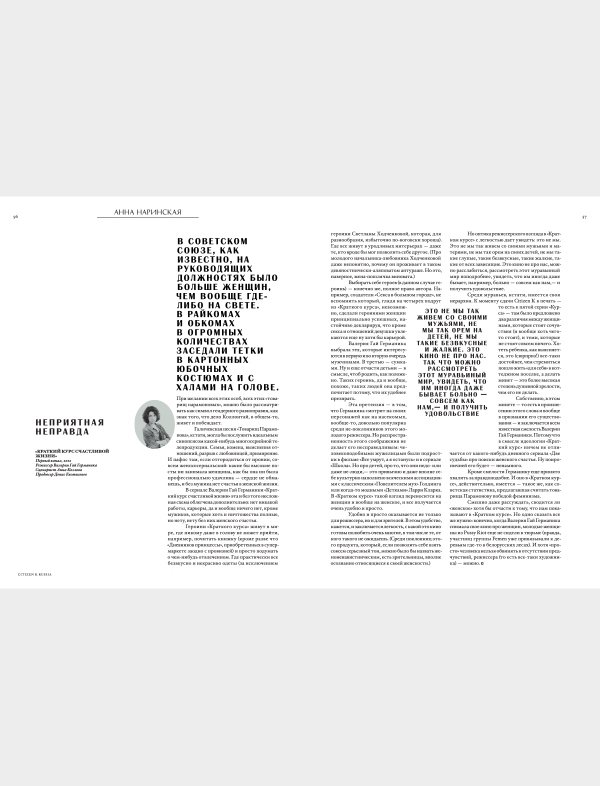
Если внутрицеховой диалог дизайнеров шрифта, типографов, графических и веб-дизайнеров более-менее налажен, то диалога с другими участниками издательского процесса — авторами, редакторами, издателями — почти не существует. Нам захотелось исправить эту ошибку.
АН: А можно задать такой вопрос? Моя личная жизнь была такая, что я жила и читала только книжки, например «Литературные памятники». Советские, но очень хорошие. Потом вдруг в какой-то момент появилось представление о том, что, кроме каких-то писателей, есть ещё что-то: панк-рок, всякие западные журналы — «Дейзд-энд-конфьюзд» (Dazed & Confused) или «Фейс» (The Face) и ещё. Там были такие шрифты, которые меня дико раздражали, но я понимаю, что это была их задача. Например, я помню, мне кто-то подарил — такой был невероятно щедрый подарок, и это, наверно, был 1999 год — подборку журнала «Фейс». Там всё было напечатано таким шрифтом. Как он называется? Шрифты состоят как бы из таких пенёчков.
ДЯ: Это пиксельный шрифт.
АН: Вероятно. Он был прямо такой, что ты ненавидел текст, который читал. Ты на него смотрел и думал: «Какая гадость! Зачем я это читаю?» Ты читал только потому, что тебе было интересно про Хлое Севиньи. И ты прямо бесился от этого. Сейчас я понимаю, что это, безусловно, было специально, это должно было так тебя раздражать. Помню, я всё время думала: «Всё хорошо в этом журнале, всё прекрасно, и темы меня интересуют, и что-то ещё, но это ужасно, зачем они это делают?»
ЮО: Представьте себе, что вы в семидесятых только что слушали группу The Beatles и вдруг почему-то видите группу Sex Pistols, а у них почему-то аппарат не настроен. А они его специально не настроили. Это, мне кажется, примерно то же самое.
АН: Я помню, как мы в «Коммерсанте» делали выпендрёжный журнал Citizen K. Там именно буквы становятся главным героем, и тогда непонятно, зачем Григорию Ревзину писать текст. Этот конфликт до сих пор для меня совершенно невыясненный.
КЧ: Дизайнеры замучили бесконечными редизайнами журналов. Ты привык к тому, что у тебя такая сетка, у тебя столько влезает на полосу. И тут очередной редизайн. «Мне надоело, всё надо поменять: новый шрифт, новое всё». Первые два номера, как правило, кровь из глаз. У меня когда-то, в бытность работы в «Плейбое», была его подшивка с 1961 по 1995 год. Как раз Дима Барбанель тогда работал арт-директором. Мы с ним любили рассматривать эту штуку. Интересно, что наборный шрифт, в общем, менялся год от года, но не чаще чем раз в пять-семь лет, а может быть, ещё реже. В основном всё биение времени задавалось акцидентными всевозможными штуками. Надо сказать, что, в принципе, даже средний Вася, когда ему показываешь разворот журнала издалека, не давая посмотреть, когда он вышел, может довольно точно назвать десятилетие просто по акцидентным шрифтам. Он может сказать: это шестидесятые, а это пятидесятые и так далее. Но по наборному шрифту это сказать совершенно невозможно. Нужно быть сильно вгруженным в тему, чтобы это угадать.
ФД: Заметим, что именно Citizen K стал тем журналом, о котором хочется вспоминать и которого не хватает. Я его как вещь именно осознаю.
Журнал CitizenK. Изображения из behance-аккаунта бывшего арт-директора Ждана Филиппова
АН: Вчера я отвезла своих родителей на некую далёкую дачу и, зайдя там в сортир, увидела стопку журналов Citizen K, которая лежала у унитаза. Я стала их листать и вспоминать, как это всё было. В частности, я помню ужас. Все это знают. На самом деле это борьба за то, что важнее, что первично — содержание или текст. Это каждый из нас знает. Приходит тебе «рыба» от дизайнера. Там написано: заголовок — два слова, подзаголовок — четыре слова, и ты хоть убейся, а выносы — строго три строчки. Ты думаешь, зачем все эти прекрасные люди, которых мы собирали, пишут все эти замечательные тексты, если дальше им говорят: «Ваш заголовок должен быть столько, подзаголовок столько, ваш текст столько, мысли столько». Потому что эпоха технической воспроизводимости вывела книгонаборщиков на совершенно другой уровень — раньше они были вообще людьми забитыми, им максимум разрешали буквицу красиво нарисовать, а дальше они бахали текст, как им сказали. Они стали изгаляться в дизайне, тем самым визуально привлекая людей плетением буквочек, и потихонечку вытеснять из массового сознания смыслы, заменяя их картинками. Именно дизайнеры, особенно из периодической печати, привели нас к этому клиповому сознанию отвратительному. Вы настоящие враги смыслов и своими красивыми шрифтами просто уничтожаете смысл.
ДЯ: А вы не чувствуете разницу жанровую, литературную, смысловую между заголовком в две строки и в пять?
АН: Например, заголовки у Стерна, которые пять строк, что они делают с этой книжкой? Это же очень смешная книжка.
ФД: Это же разные миры.
АН: Честно говоря, скажу, что нет, я не вижу жанровой разницы в заголовке «Эх, ухнем» и в заголовке «Эх, ухнем, потому что трали-вали».
ФД: Может быть, тем не менее разница есть.
ДЯ: «Глава первая. Урбанизм как образ жизни» и «Глава первая, в которой рассказывается, как герой бла-бла-бла». Это же разные совершенно вещи. В моей картине мира дизайнер советуется с редактором, какого жанра у него будет заголовок: повествовательный, назывной, игровой.
АН: Наверное, в практике это выходит совершенно по-другому, потому что обычно это связано с тем, какая стоит картинка и ещё что-нибудь и как это всё друг с другом монтируется.
ФД: Это вопрос к редактору, который связующее звено между дизайнером и автором текста. Если ты Стерн и хочешь написать заметку в газету «Коммерсантъ» или журнал Citizen K, то ты пишешь один текст — и к нему будет один заголовок. Если ты Стерн, который пишет роман, то это будет другой текст и другой заголовок. Дизайнер (тот же самый, может быть) будет решать иным образом задачу этого заголовка и вёрстки этого текста. Иначе я как читатель, открывающий журнал Citizen K, не буду знать, что я получу завтра и послезавтра. Потому что сегодня ты решила, что хочешь сказать мне про то, как схватила горничную за …, на семнадцати страницах, а в другой раз ты захочешь мне сообщить какую-то короткую мысль. Я перестану читать это издание, потому что оно непонятно.
АН: Нет, мне кажется, ты страшно идеализируешь.
КЧ: Это идеальный журнал в идеальном мире, который делается идеальные полгода, и идеально все со всеми советуются.
ЮО: На самом деле Филипп сейчас описал журнал «Большой город», который делался ровно таким образом.
АН: Ладно, не будем врать. Недавно я наблюдала твою большую переписку, где твой контрагент, видный и всем известный, прекрасный российский редактор, вас страшно ругал, что вы какие-то слова берёте в кавычки. Он считает, что вы просто ничего сказать не можете.
КЧ: Я ненавижу наринские скобки.
АН: Скобки — это не то.
КЧ: В последнее время появляются скобки внутри скобок.
ФД: Тире — ты любишь тире?
АН: Мы с Цветаевой любим тире.
КЧ: Я обожаю тире. У меня всё сделано через тире.